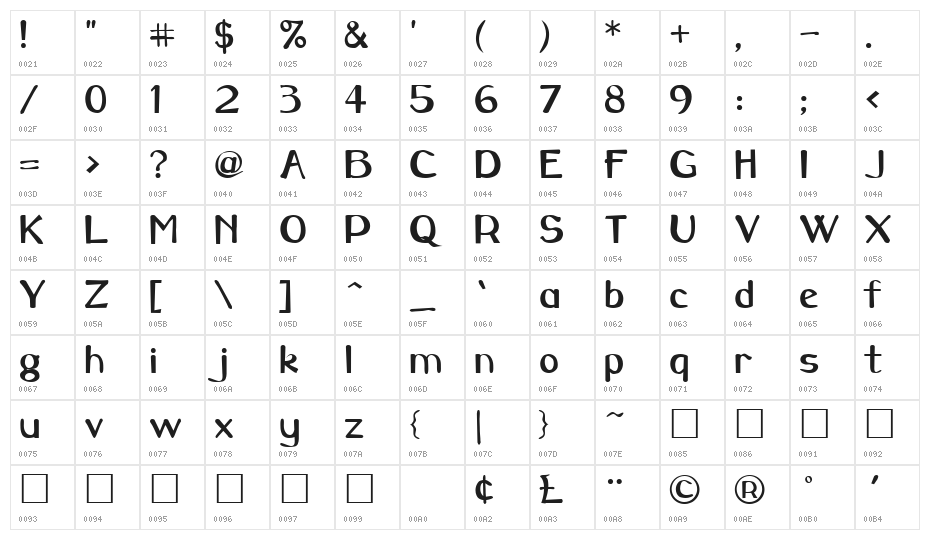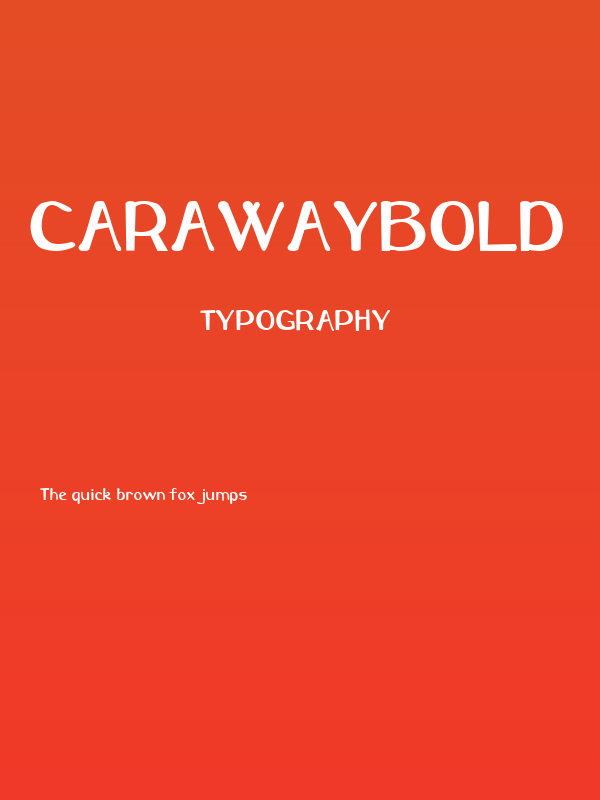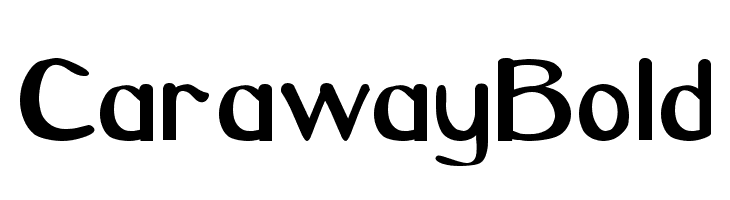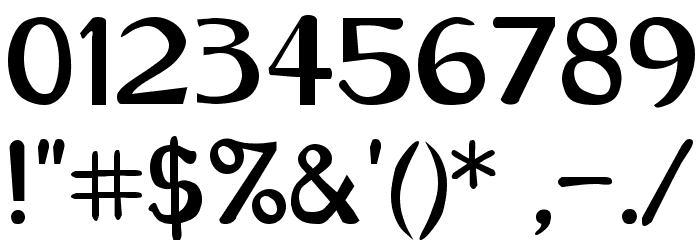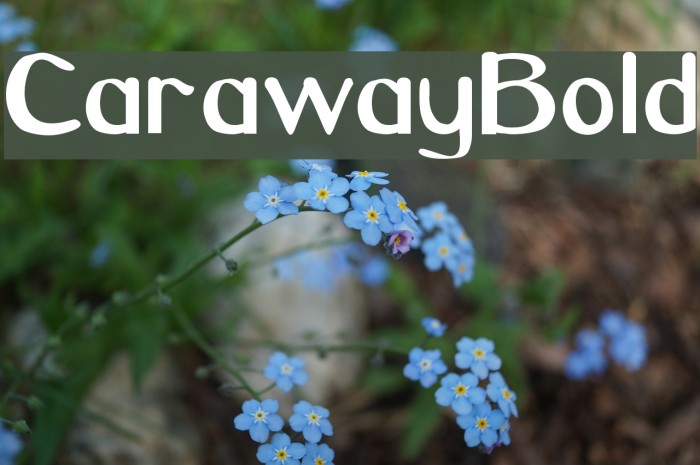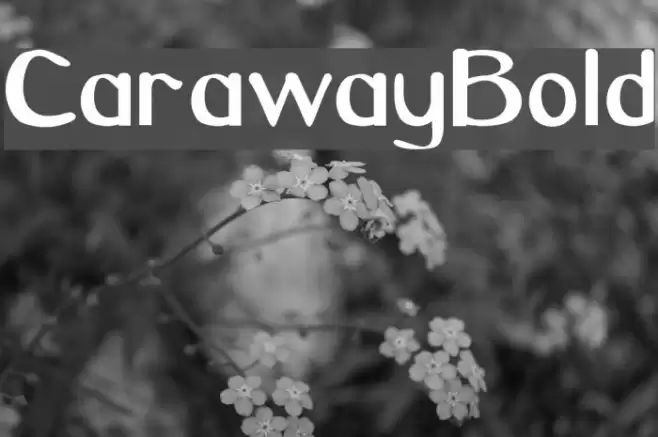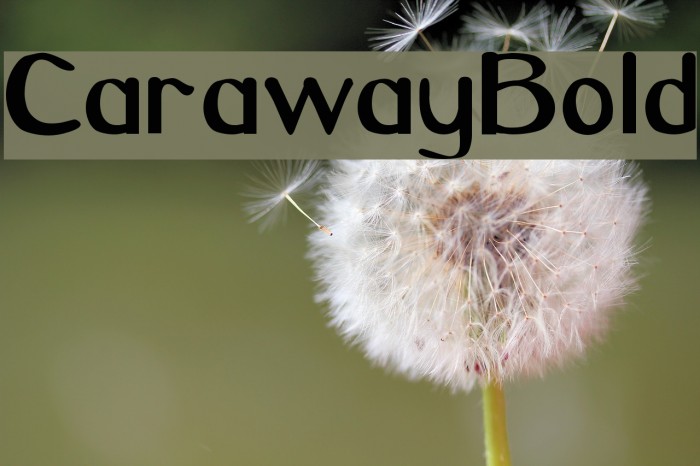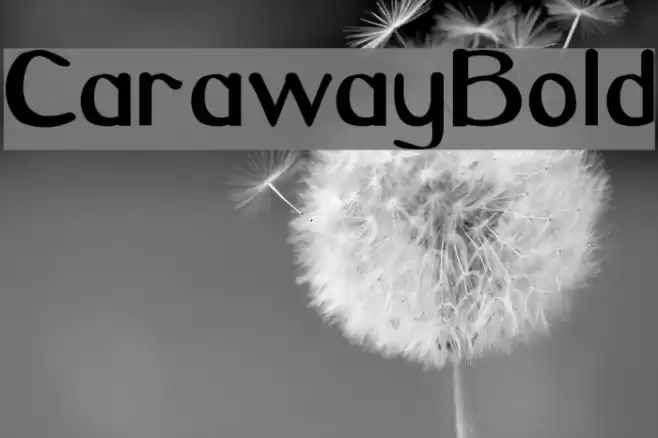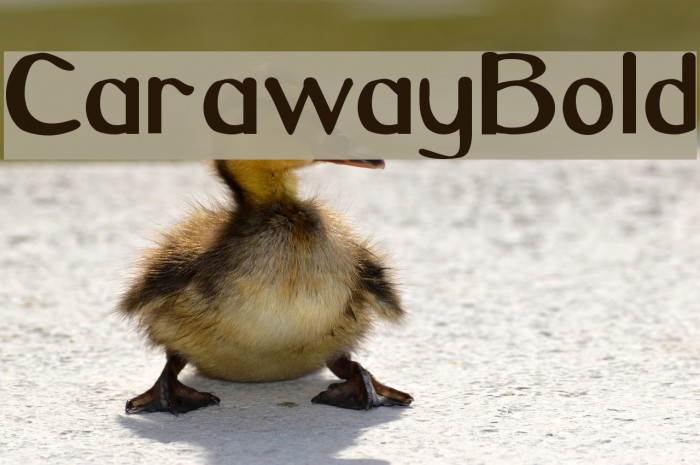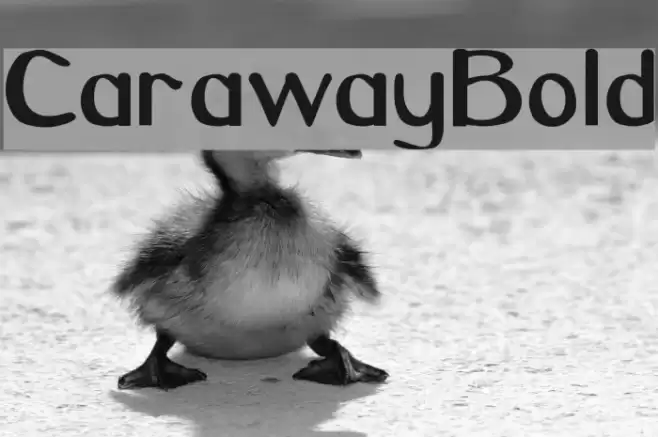
CarawayBold Font
| Caso de uso | Headlines, Logos, Branding |
| Proyectos propuestos | Ideal for branding, advertising, children's books, and digital media where a friendly and approachable typeface is desired. |